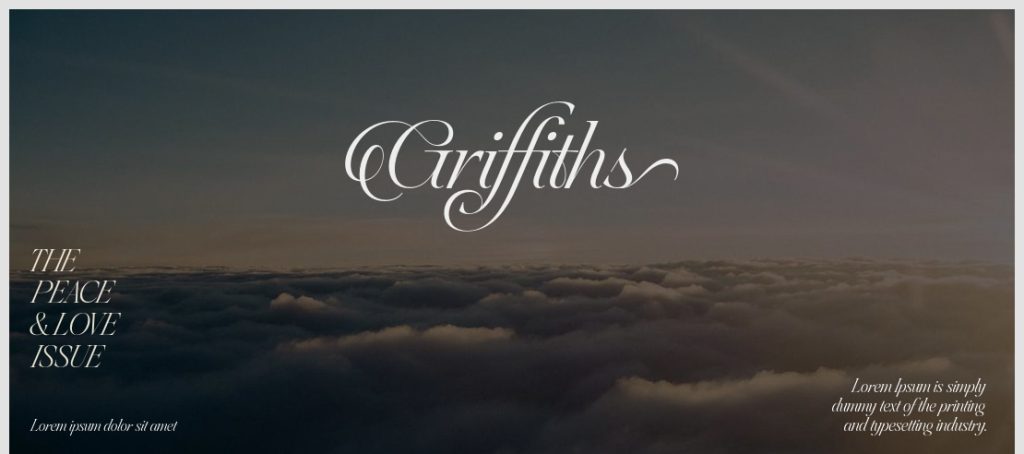
Tác giả: Attract Studio
Phân loại: Sang trọng, lịch lãm
Kiểu chữ: Serif
Font 1FTV Griffiths là một kiểu chữ mạnh mẽ và sang trọng, mang đậm phong cách cổ điển nhưng vẫn giữ được vẻ hiện đại. Phông chữ này, thuộc bộ font chữ 1FTV với các đường nét sắc sảo và cân đối, font này rất phù hợp cho những thiết kế đòi hỏi sự lịch lãm và đẳng cấp, chẳng hạn như logo thương hiệu, tiêu đề, poster hoặc các ấn phẩm quảng cáo cao cấp. Font 1FTV Griffiths không chỉ giúp tạo điểm nhấn cho thiết kế với tính thẩm mỹ tinh tế mà còn truyền tải cảm giác chuyên nghiệp và uy tín, làm cho bất kỳ sản phẩm nào cũng trở nên nổi bật và thu hút.